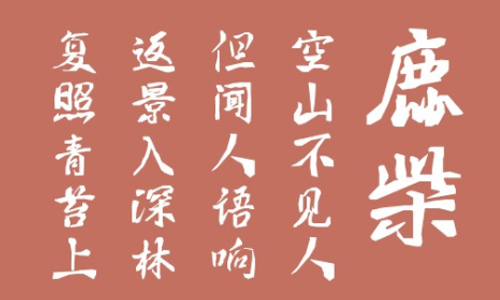
南構(gòu)霸虎勁草字體是南構(gòu)字庫(kù)推出的一款草書(shū)字體,南構(gòu)霸虎勁草字體剛勁有力。經(jīng)過(guò)作者的反復(fù)修改,并經(jīng)字體家團(tuán)隊(duì)多個(gè)環(huán)節(jié)的精心制作,最終呈現(xiàn)為6763個(gè)漢字的優(yōu)質(zhì)字庫(kù),歡迎大家前來(lái)下載使用。